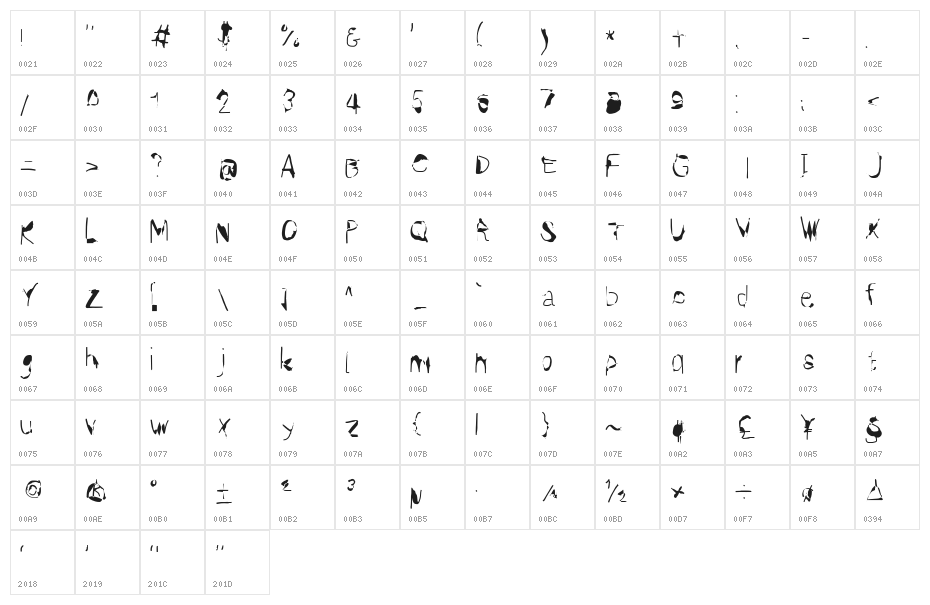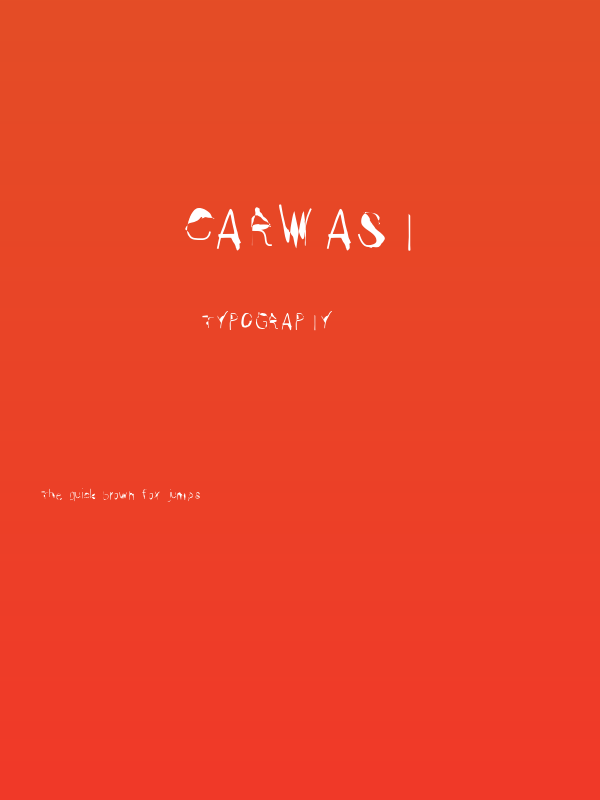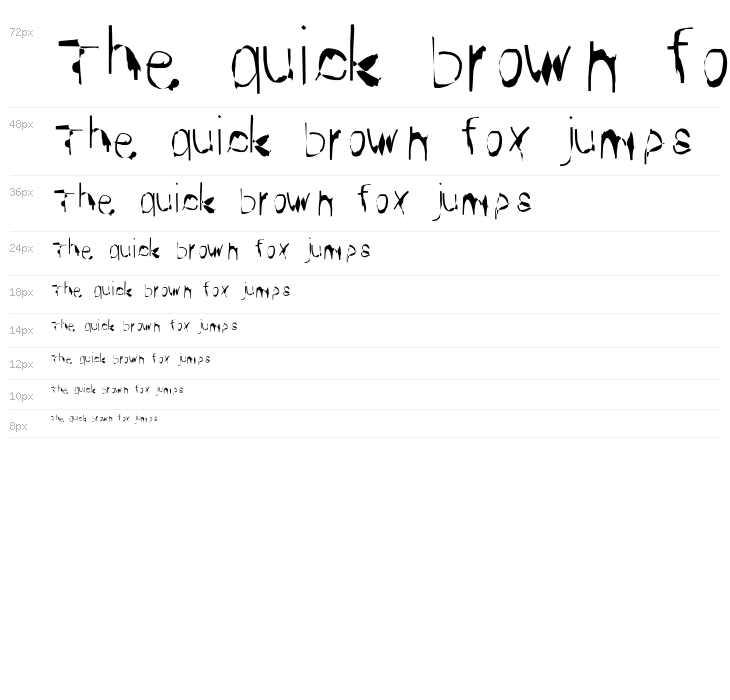
CarWash Font
✎ Distorted Eroded
| Kategorien | Distorted Eroded |
| Gesamtstil | Grunge, Artistic |
| Anwendungsfall | Logos, Posters, Album Covers |
| Vorgeschlagene Projekte | Ideal for album covers, streetwear branding, graffiti art, and edgy poster designs. |